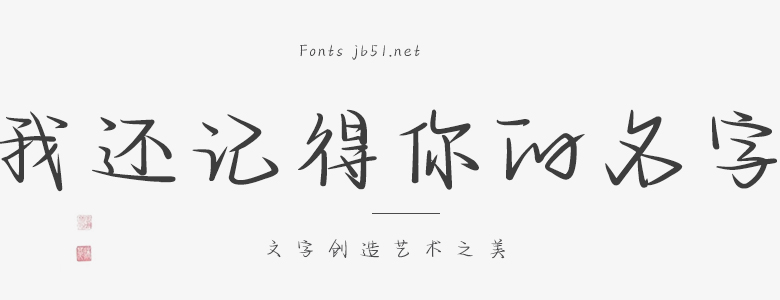
我還記得你的名字是一款極具個性的手寫字體,它的設(shè)計靈感來源于大自然和日常生活中的紋理和線條。字體線條流暢,富有彈性,給人一種輕松隨性的感覺。該字體獨特的筆畫設(shè)計,猶如手寫的筆跡,增加了字體的親切感和人性化。 我還記得你的名字字體適用于各種不同的設(shè)計和排版環(huán)境,無論是印刷品、廣告牌還是電子設(shè)備,都能展現(xiàn)出其獨特的魅力和風(fēng)格。它是一款既能滿足商業(yè)應(yīng)用的需求,又能體現(xiàn)設(shè)計師個人風(fēng)格的優(yōu)秀字體。 當(dāng)你使用這款字體時,你會感受到它所傳遞的情感和故事。它像是一個朋友在紙上留下的溫馨留言,或是戀人在便簽上寫下的甜蜜字句。每一筆、每一畫都似乎在講述著一個美好的回憶,讓人在閱讀的同時感受到心靈的觸動。 總的來說,我還記得你的名字是一款富有情感和故事性的手寫字體,它獨特的設(shè)計風(fēng)格和靈活的應(yīng)用性使其成為設(shè)計師們的必備之選。